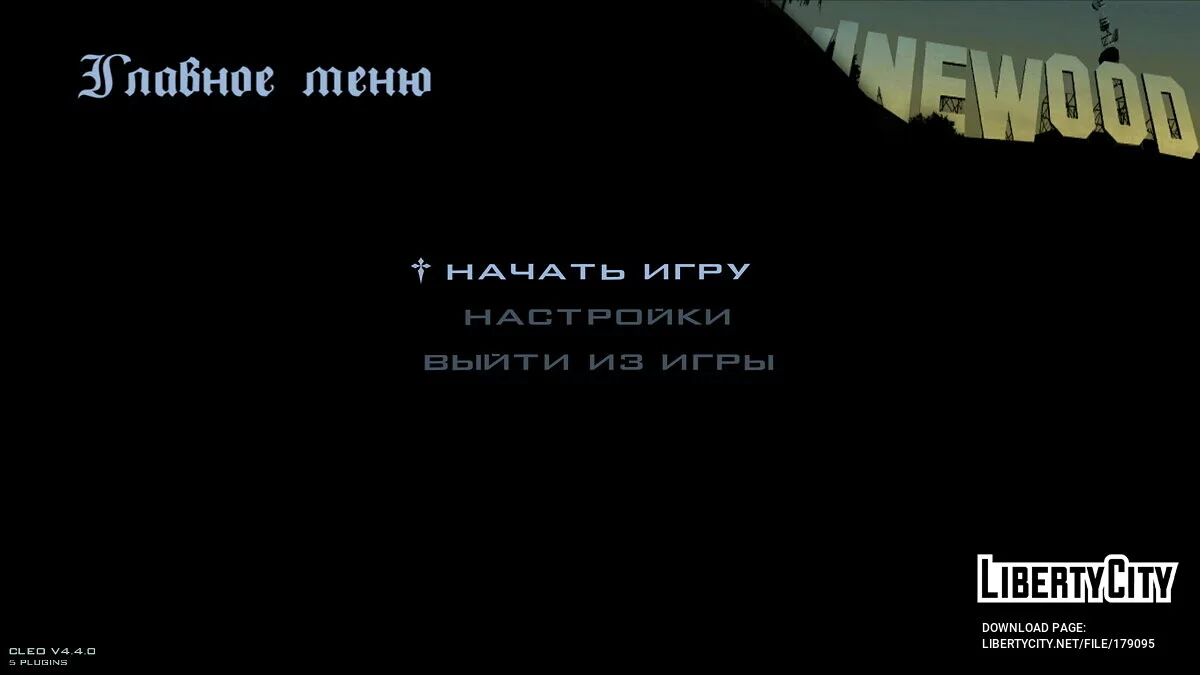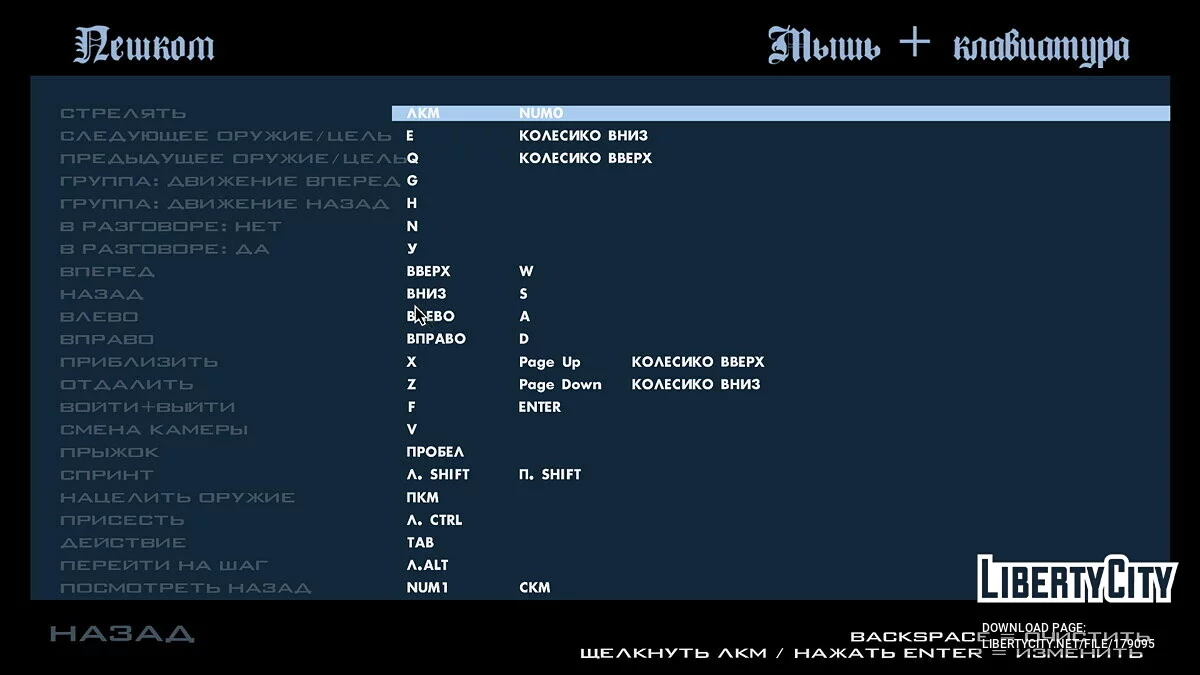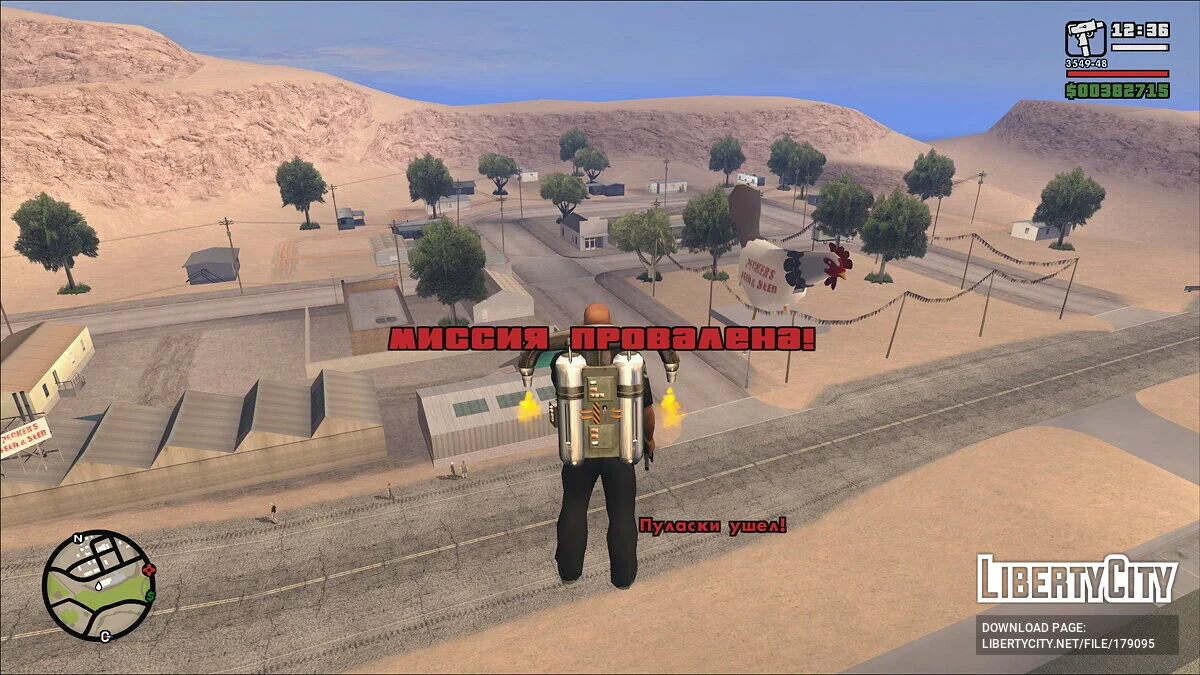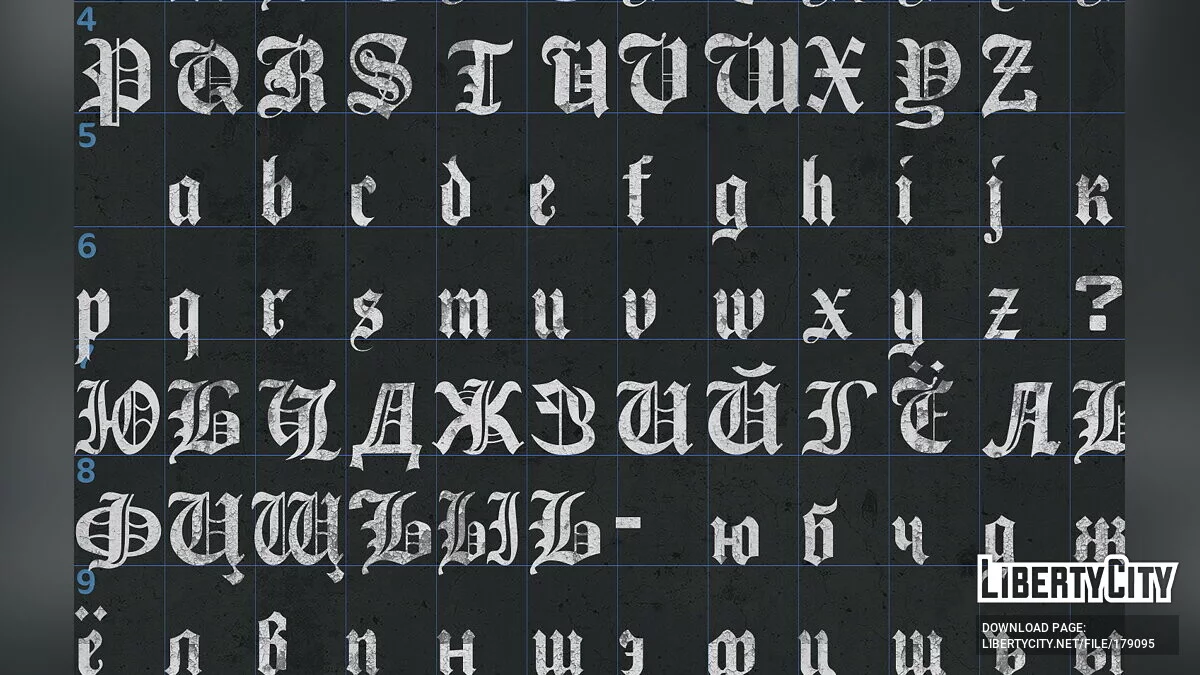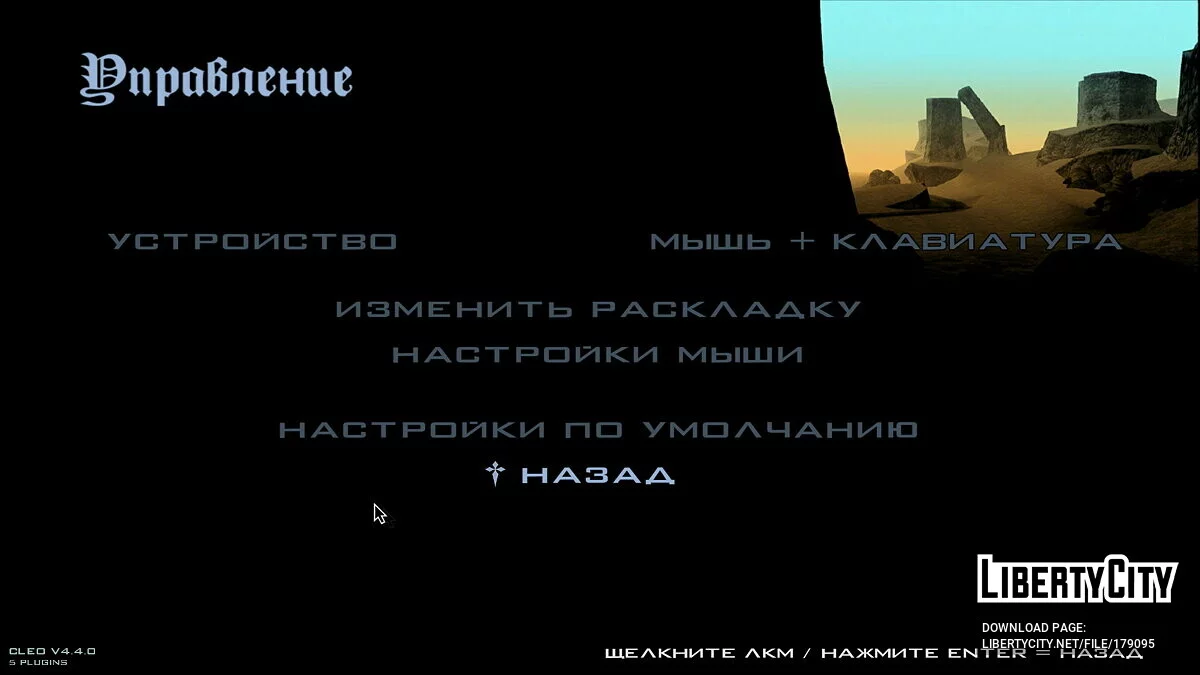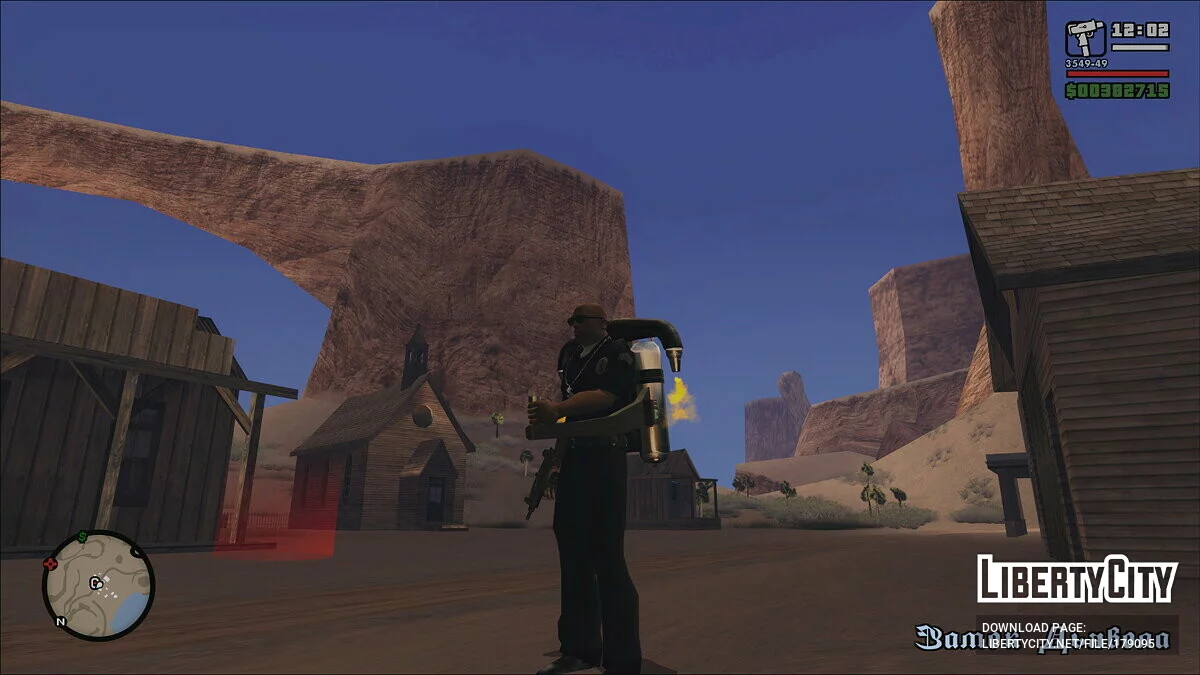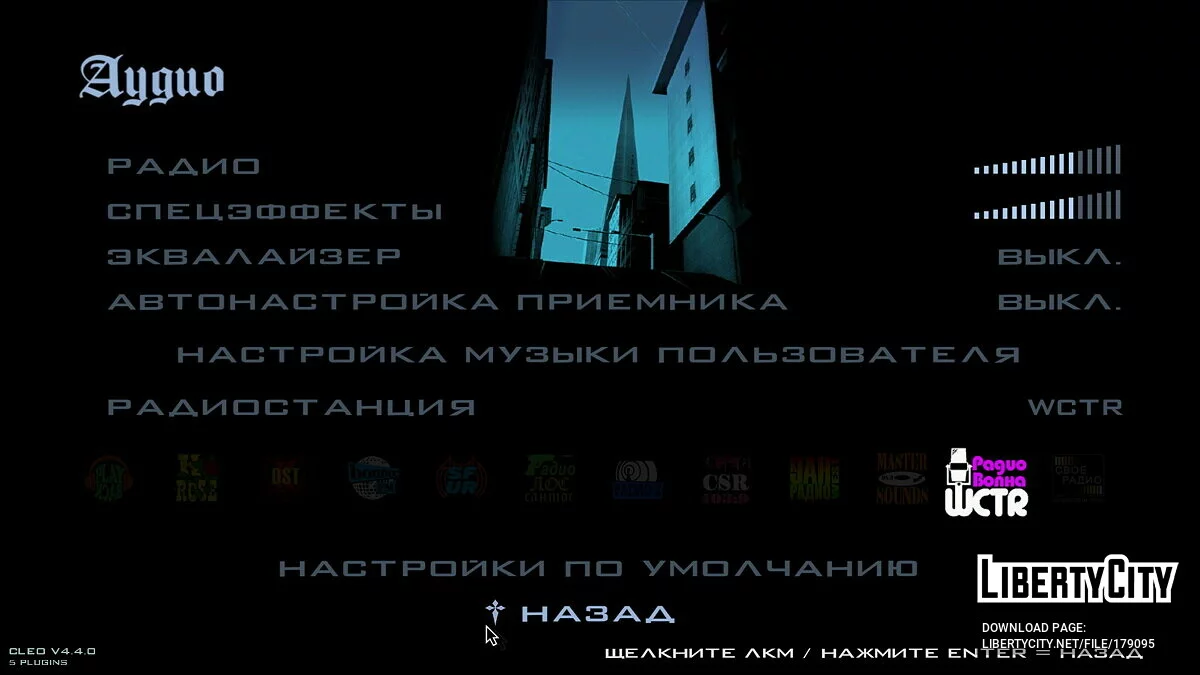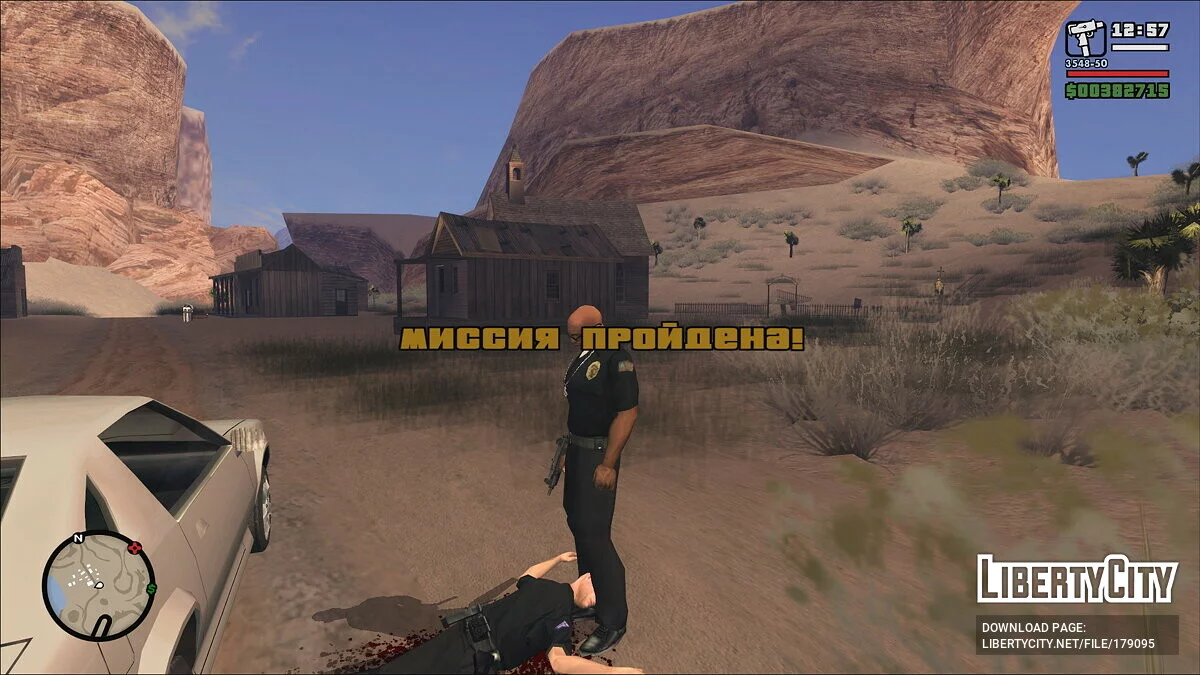
HD-шрифты для русификатора 1С
Это моя первая попытка что-то сделать со шрифтами (как-то их улучшить).
Немного расставил символы, провел цветокоррекцию, некоторые символы постарался сделать, как в оригинале. Один шрифт проверил на ровность строк и равную высоту символов. Через 2 часа мозг лопнул. Больше я проверки пока устраивать не буду.